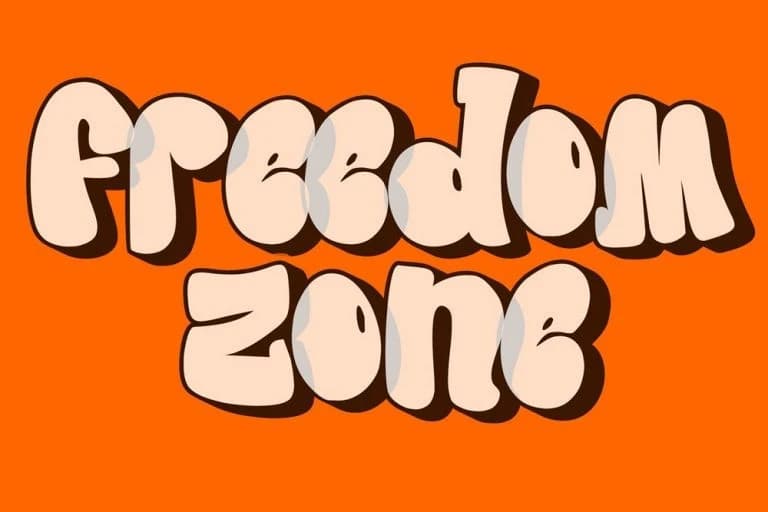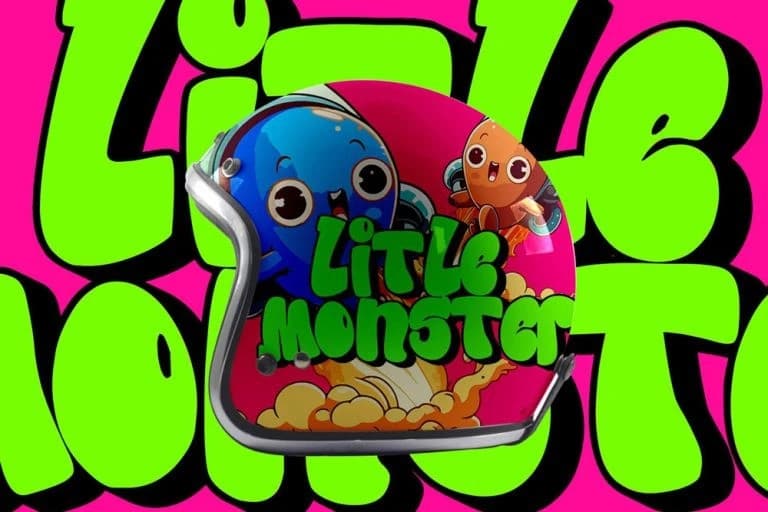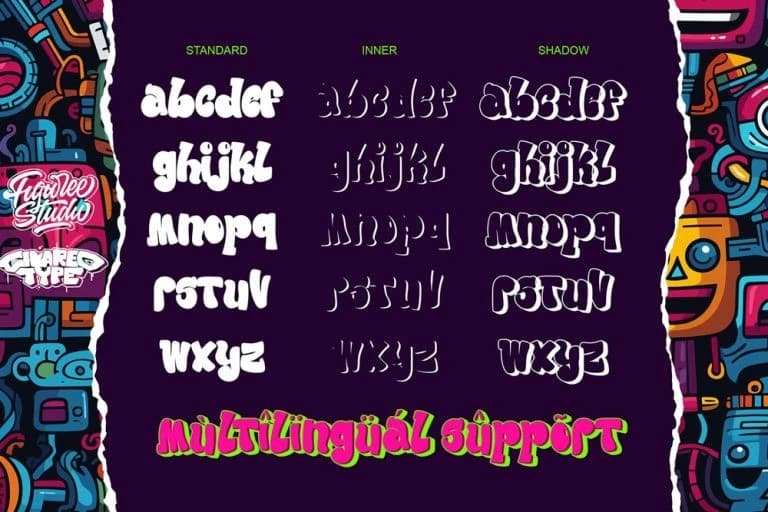
Urban Maxim Font
Urban Maxim Font, güçlü 3D derinlik ve katmanlı kentsel estetikler sunmak üzere tasarlanmış cesur ve fütürist bir graffiti yazı tipidir. Etki yaratan tipografi talep eden yaratıcılar için tasarlanmış bu 3D graffiti yazı tipi, basit metni görsel olarak güçlü kompozisyonlara dönüştürür.
Urban Maxim Font cesur ve fütüristik bir grafiti fontudur; güçlü bir 3D derinlik ve katmanlı kentsel estetikler sunmak üzere tasarlanmıştır. Etkileyici tipografi talep eden yaratıcılar için tasarlanan bu 3D grafiti fontu, basit metni görsel olarak güçlü kompozisyonlara dönüştürür.